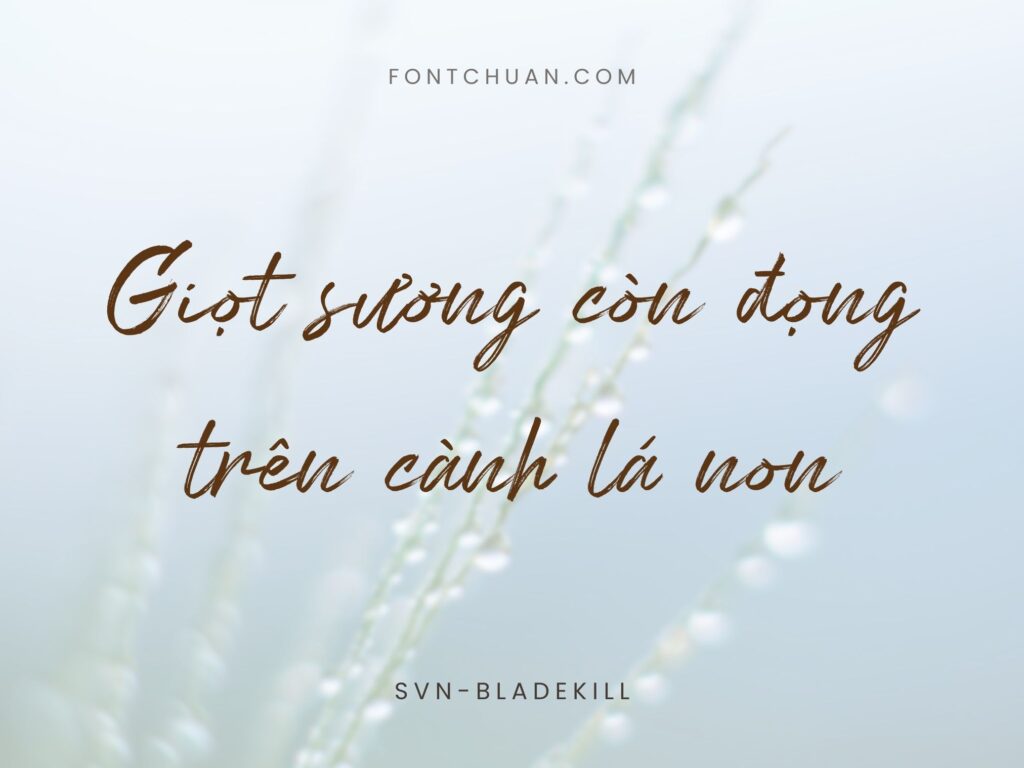
Font SVN Bladekill Dạng Brush Việt Hóa
Tác giả Font: Muhammad Sirojuddin
Font SVN-Bladekill là phiên bản Việt hóa của kiểu chữ Bladekill, được thực hiện bởi Styleno.1 Fonts. Bladekill là một phông chữ script dạng cọ vẽ, được viết một cách tự nhiên và nhanh chóng, tạo nên vẻ đẹp trên nhiều thiết kế yêu cầu phong cách cá nhân hóa. Font này lý tưởng cho các dự án như thiết kế logo, thiệp mời, tiêu đề và các ấn phẩm truyền thông.
SVN-Bladekill phù hợp cho các dự án thiết kế yêu cầu sự cá nhân hóa và sáng tạo. Font này có thể ứng dụng như một Font chữ spa, mang đến cảm giác mềm mại, thanh lịch và thư giãn cho các thương hiệu chăm sóc sức khỏe, làm đẹp và spa. Đồng thời, font cũng được tận dụng hiệu quả trong các ngành thiệp cưới và ẩm thực để tạo điểm nhấn nổi bật trong thiết kế. Nhờ sự linh hoạt, SVN-Bladekill còn thích hợp cho các sự kiện như Tết, Valentine, Sinh nhật và các lễ hội khác.